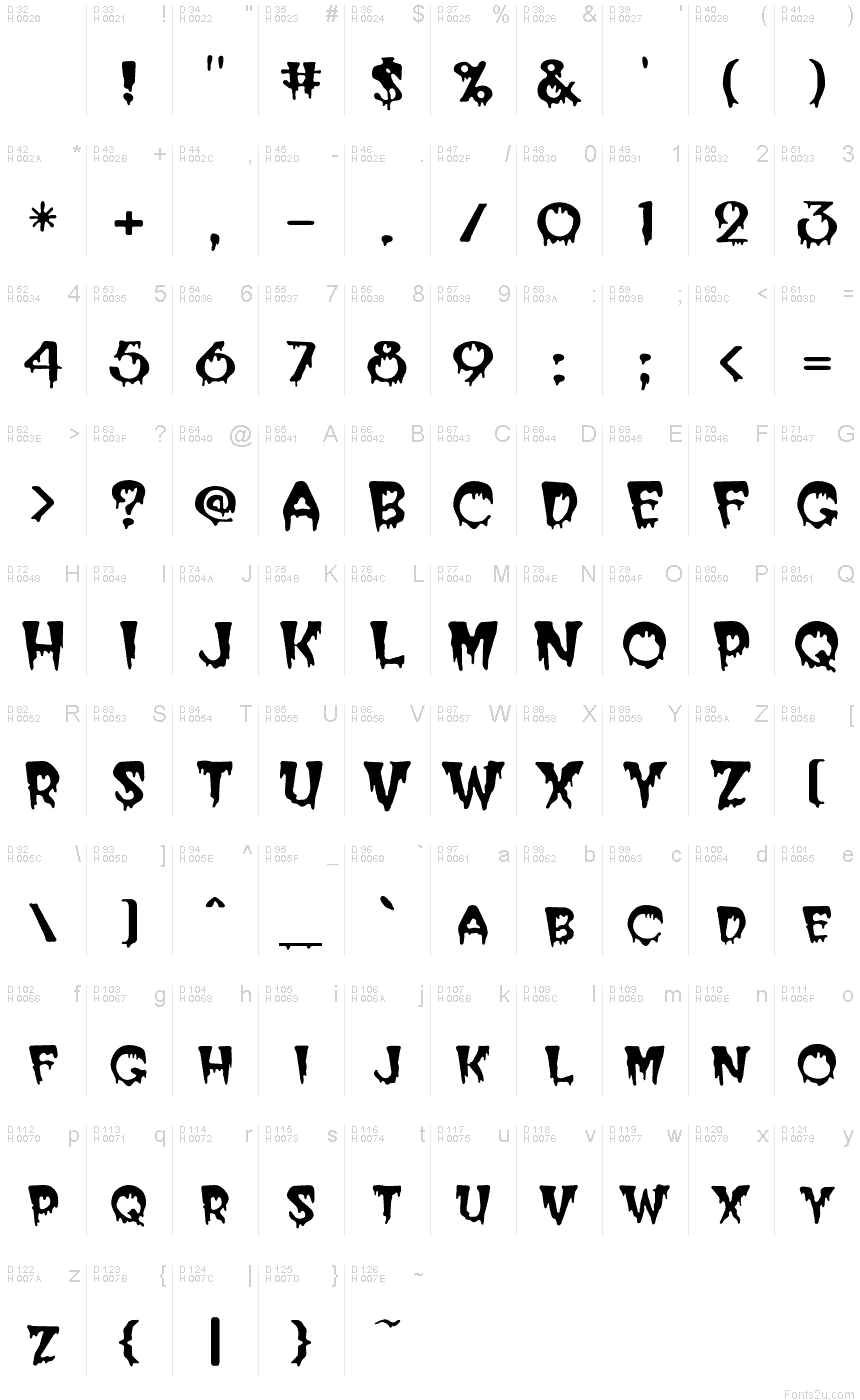
PostCrypt è un font gratuito in stile horror con maiuscole spesse e colanti, che richiamano subito le atmosfere dei poster dell'orrore. Le lettere appaiono gonfie e gocciolanti, con sommità arrotondate e colature che conferiscono al carattere un aspetto umido, gommoso e un po' teatrale, piuttosto che crudo.
È una scelta naturale per volantini di Halloween, branding per attrazioni da brivido, copertine di fanzine horror, packaging originali e titoli in stile camp, dove la silhouette gocciolante comunica il messaggio principale. Essendo un font gratuito, funziona meglio in brevi passaggi – titoli grandi, loghi o iniziali – perché l'effetto viscoso è il punto focale e rende al meglio quando si lascia alle lettere lo spazio necessario.